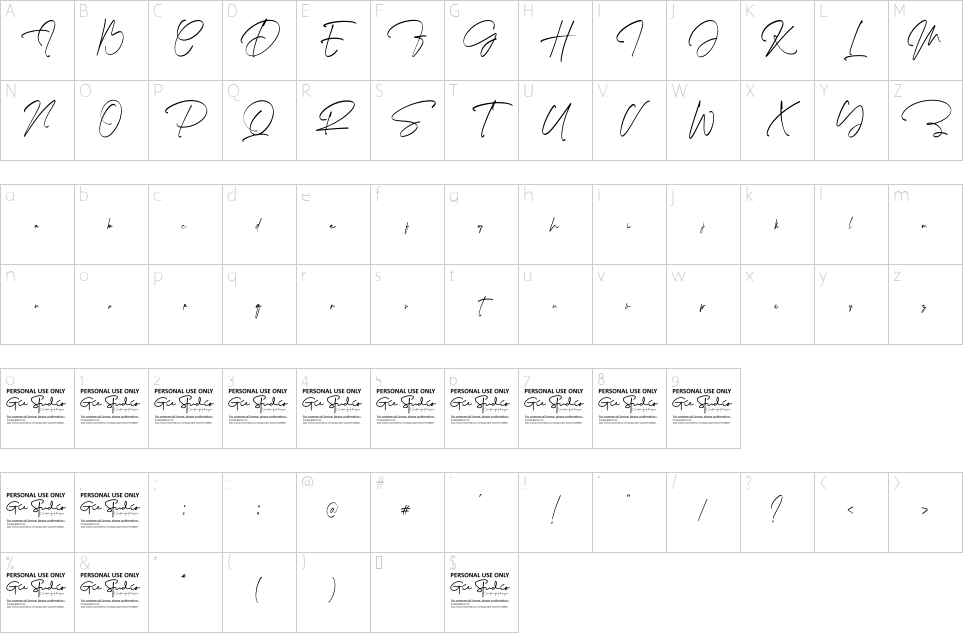
Penthagon é uma fonte moderna e elegante que se destaca entre as outras, trazendo uma abordagem minimalista e sofisticada para o seu trabalho. Inspirada por designers de arquitetura, esta fonte se adapta perfeitamente a criações de design gráfico e publicidade, oferecendo um texto com detalhes precisos e elegância. Seja você designer de nomes, de logotipos ou de anúncios, Penthagon é uma escolha inteligente para trazer um toque de sofisticação à sua obra. Desenvolvida pela Gie Studio, esta fonte gratuita vem disponível para Windows e Mac, e já foi baixada por 3,514 usuários. Se você procura uma fonte que combine precisão e estilo, Penthagon pode ser exatamente o que você procura.